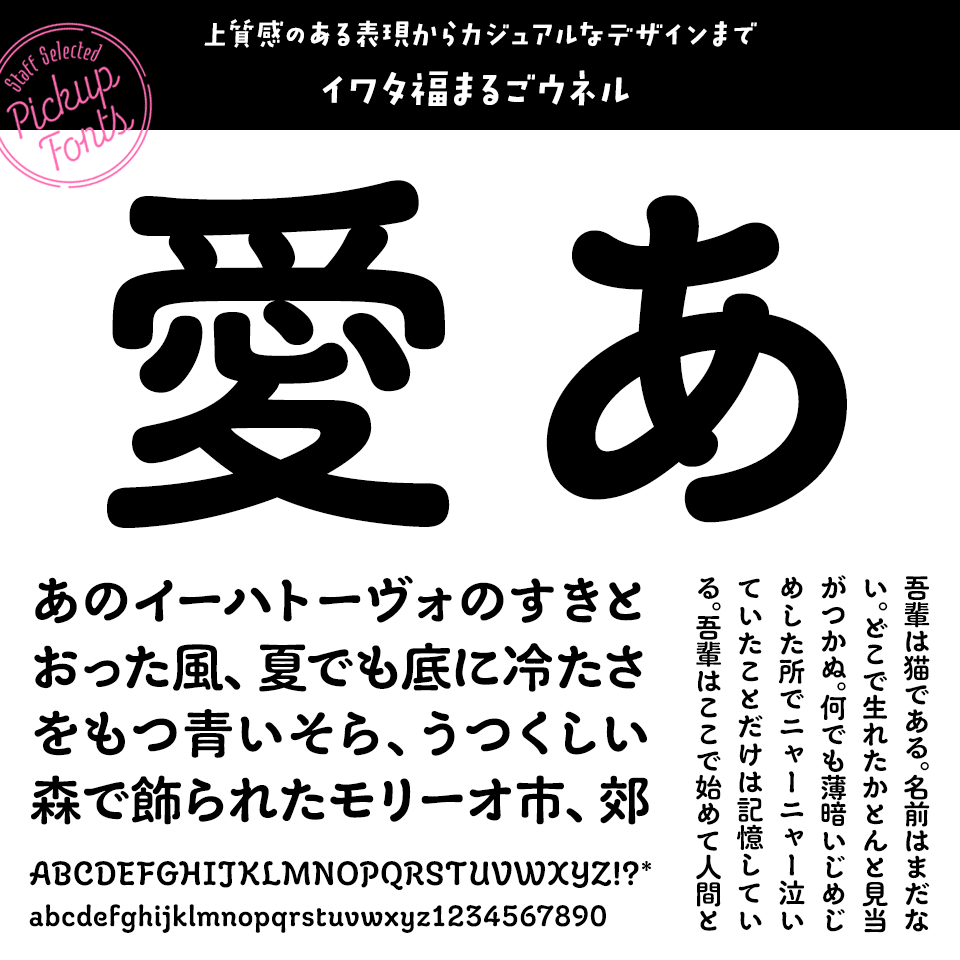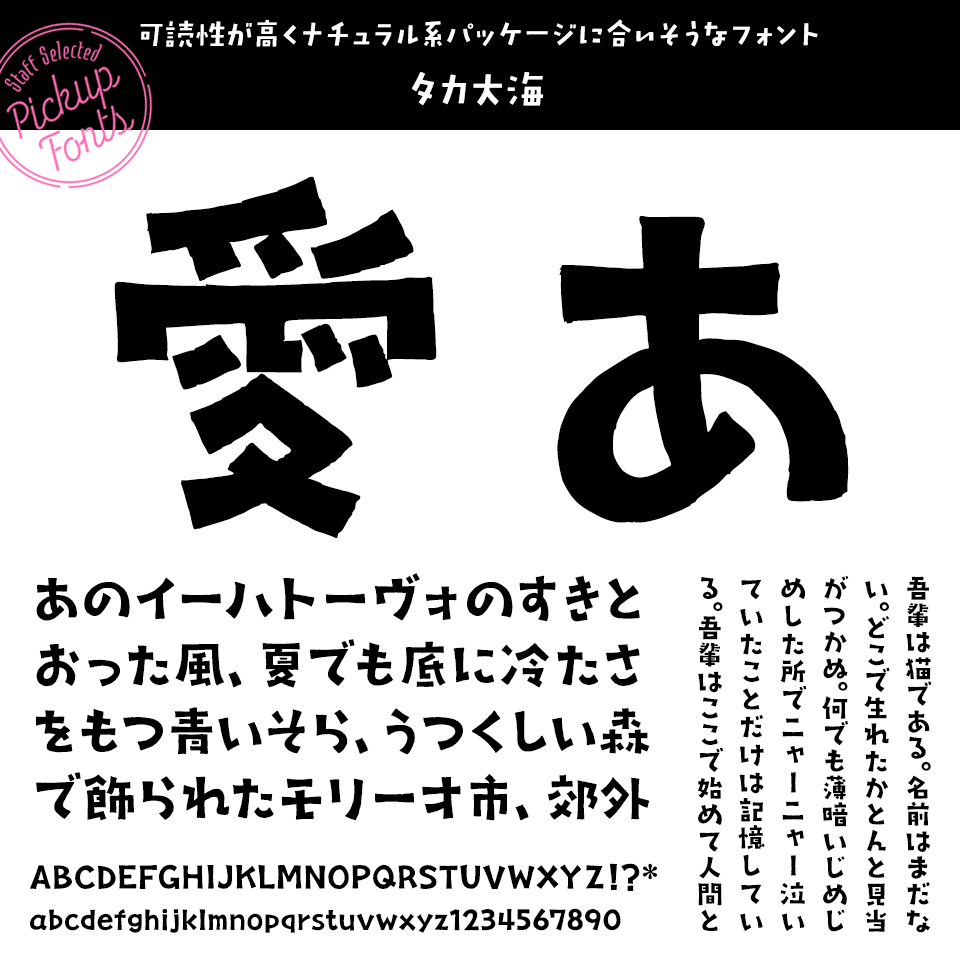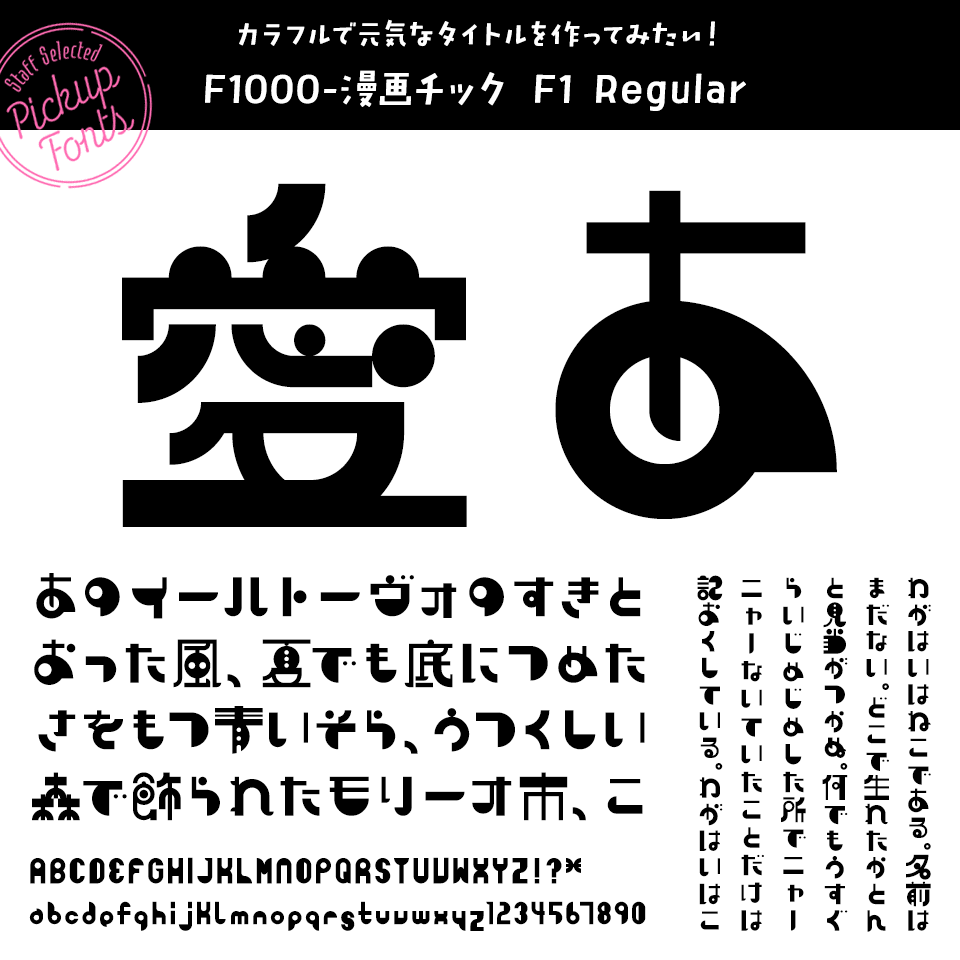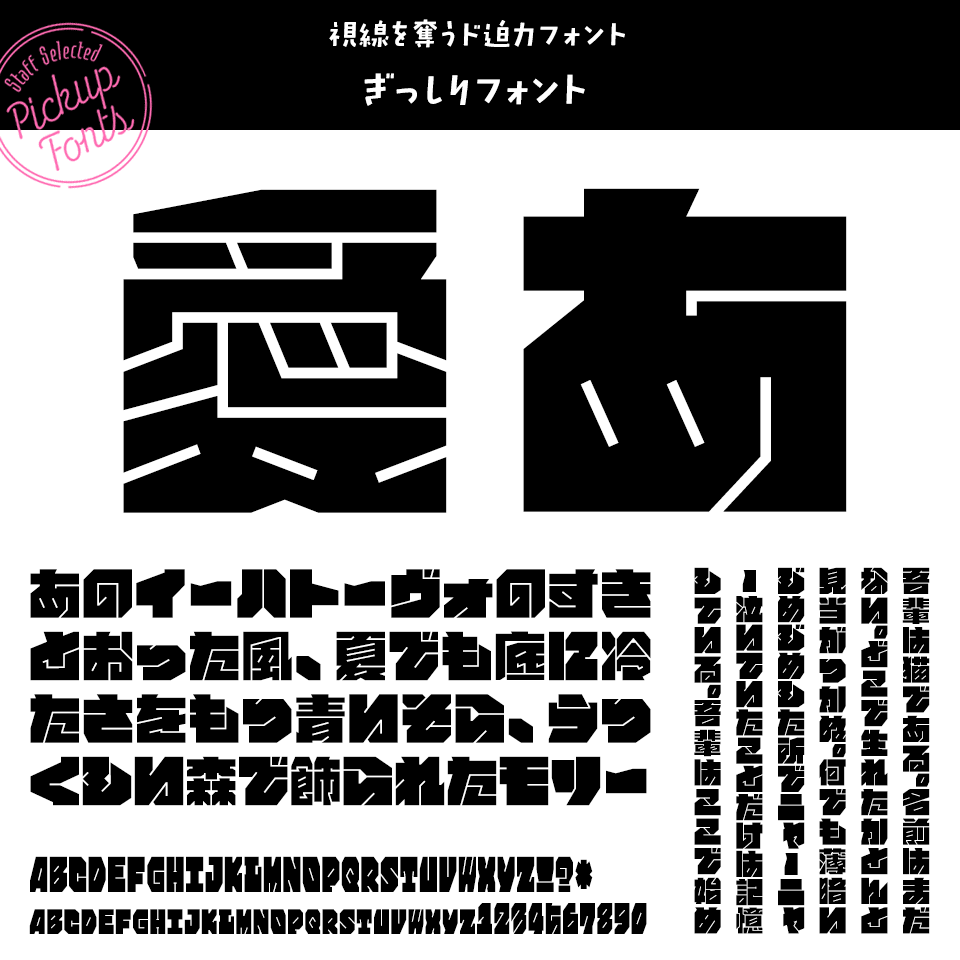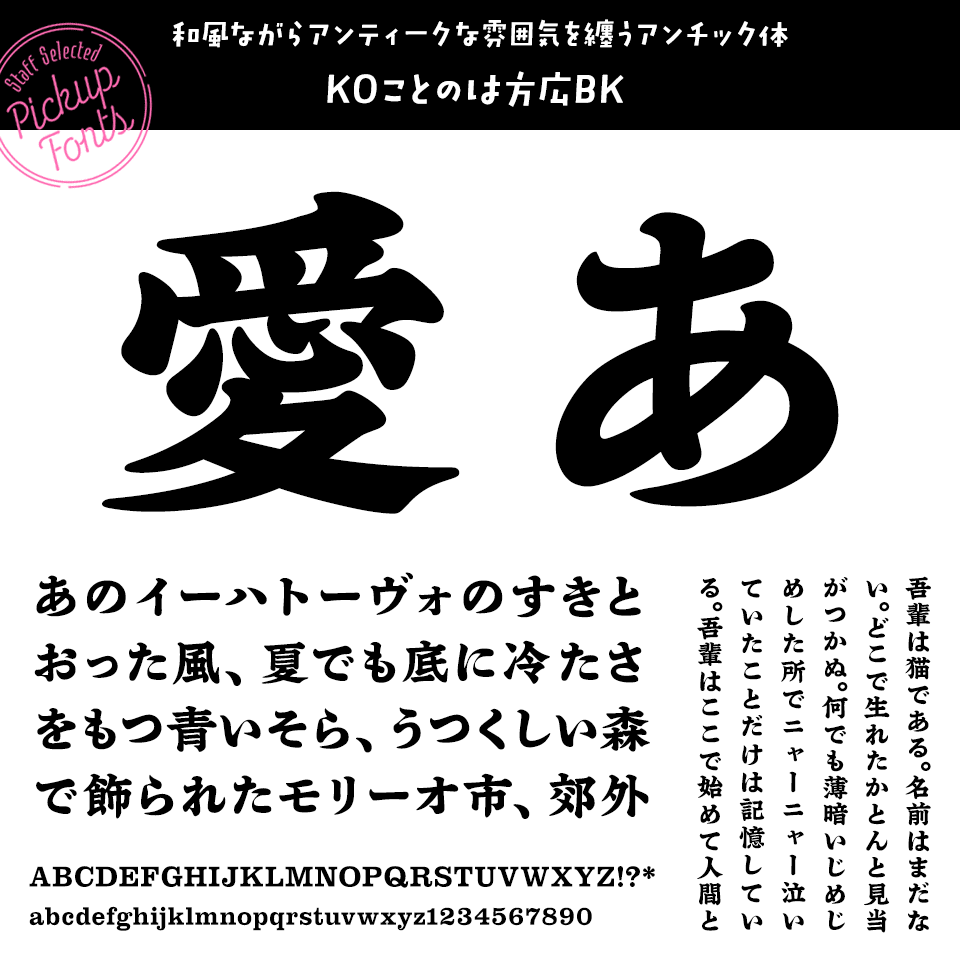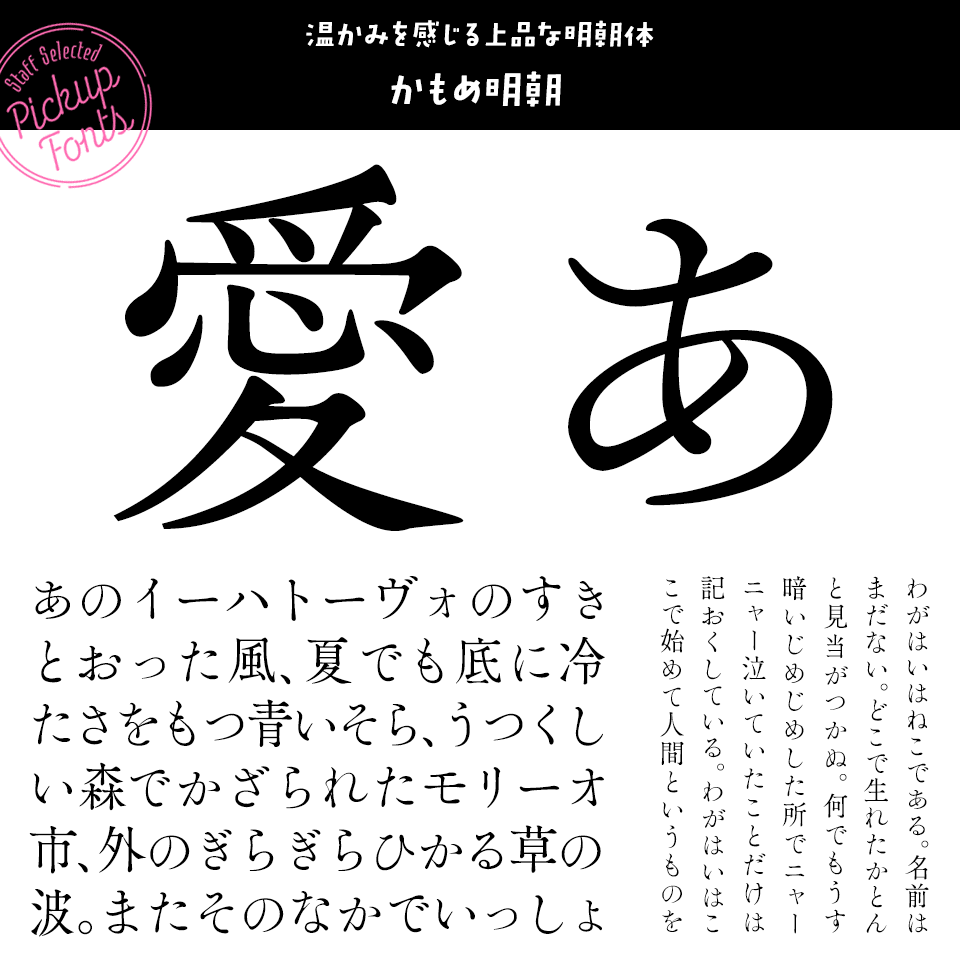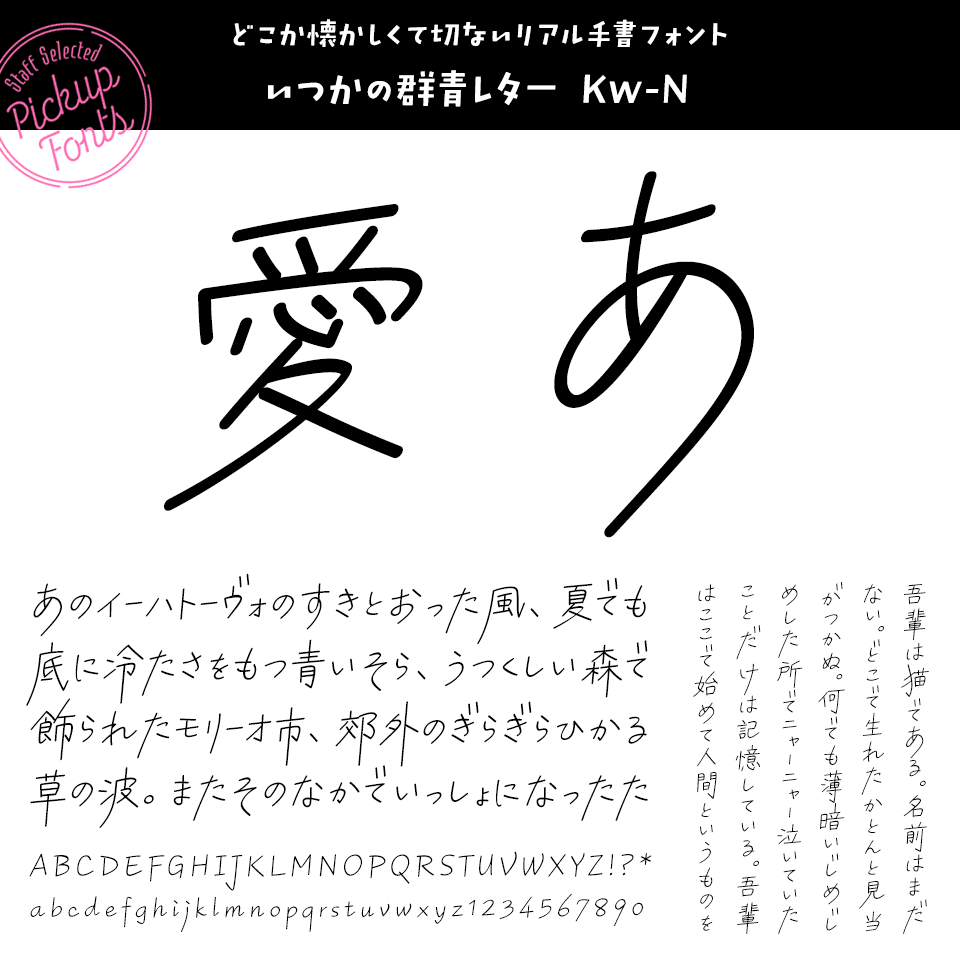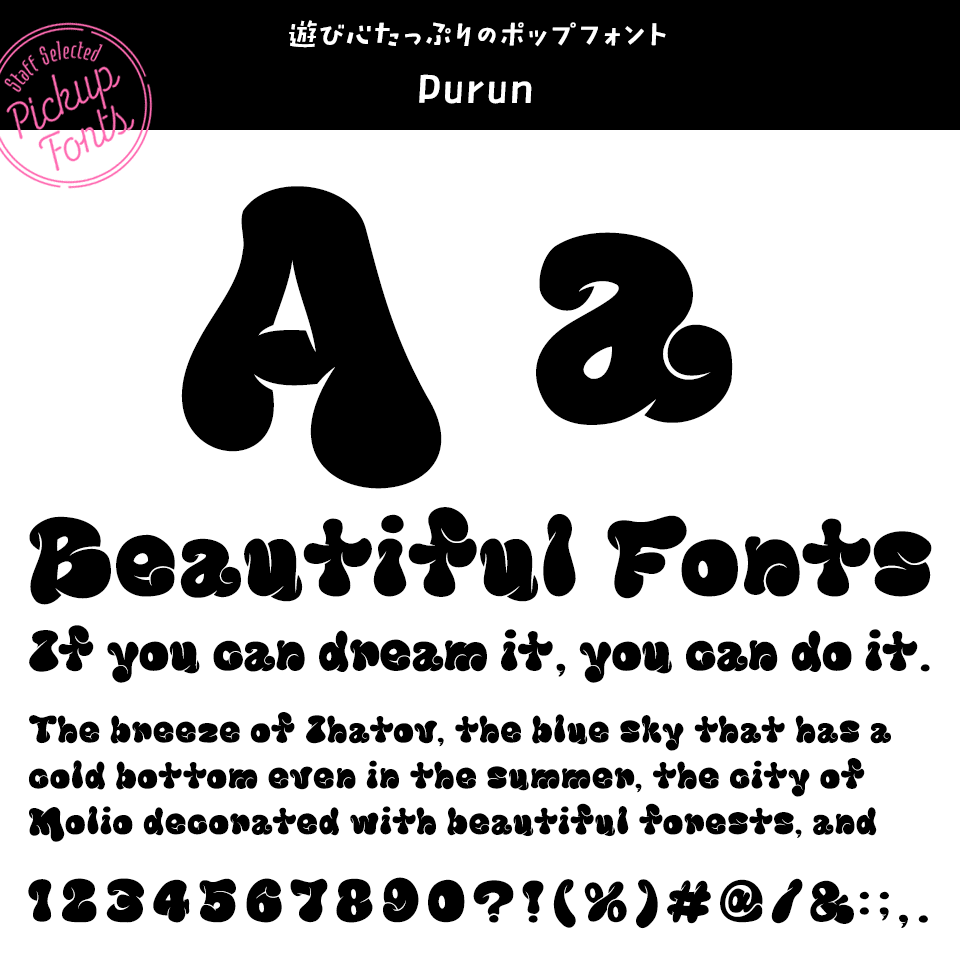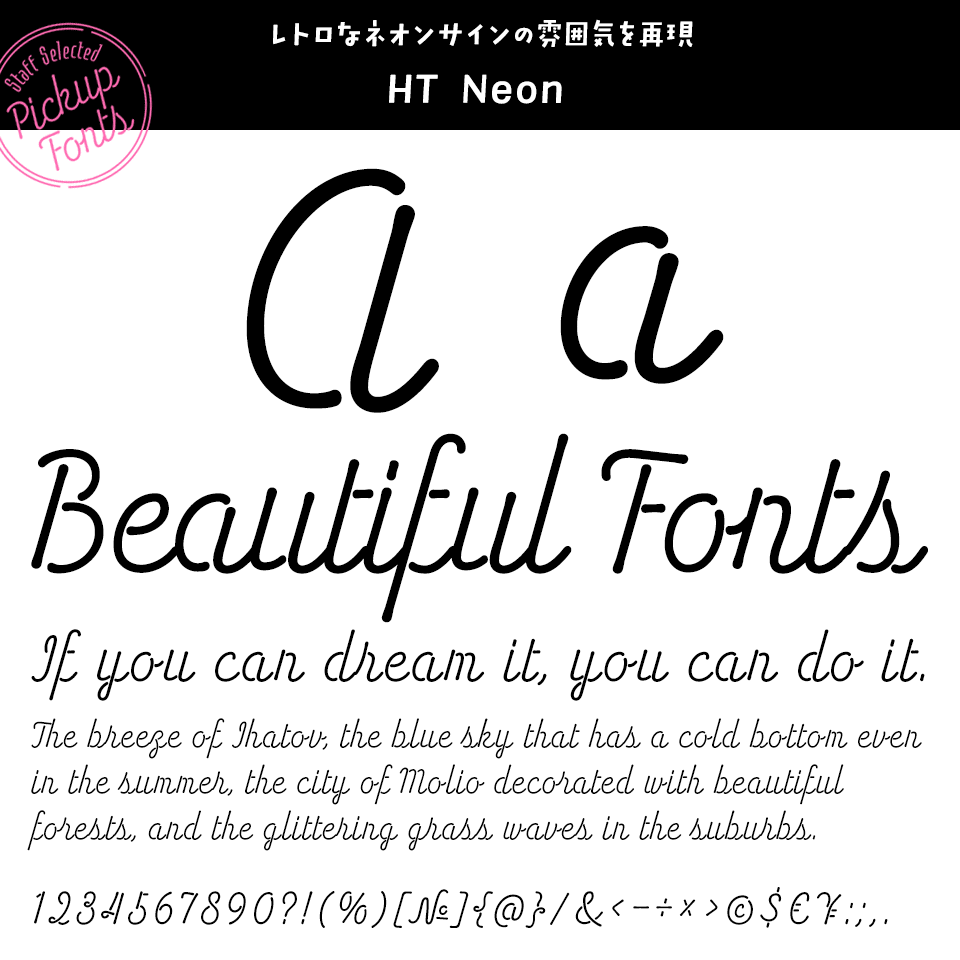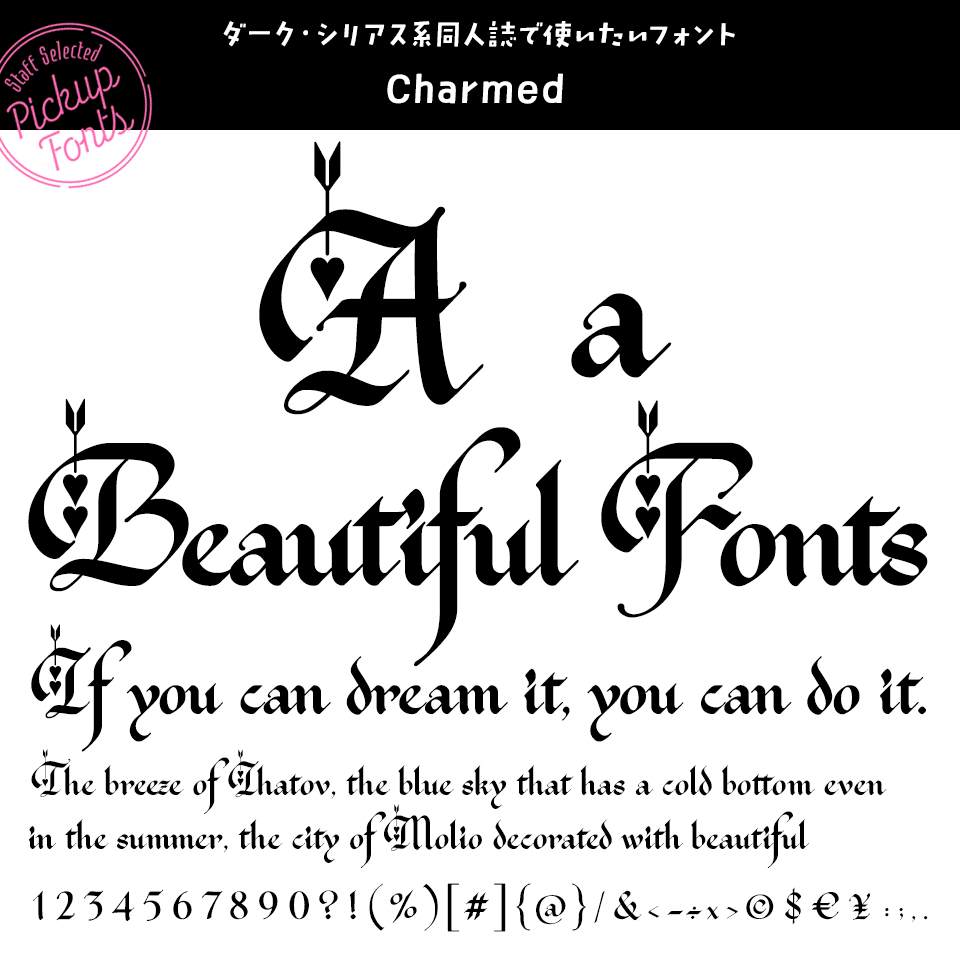
デザポケスタッフの個人的に好きなフォント イワタ福まるごウネル
上質感のある表現からカジュアルなデザインまで
デザポケスタッフの個人的に好きなフォント イワタ福まるごウネル
福まるごの「もっちりぽってり」としたやさしい丸みに、ゆるやかな揺らぎのニュアンスをプラス。上品な印象はもちろん、少しラフで親しみやすいデザインにもなじむ、表情豊かな書体です。
デザポケスタッフの個人的に好きなフォント タカ大海
可読性が高く、ナチュラル系パッケージに合いそうなフォント
デザポケスタッフの個人的に好きなフォント タカ大海
素朴で温かみのある線が特徴で、アナログ感のあるフォント。個性を出したい場面で存在感を発揮する、印象的な手書き風フォントです。
デザポケスタッフの個人的に好きなフォント F1000-漫画チック F1 Regular
カラフルで元気なタイトルを作ってみたい!
デザポケスタッフの個人的に好きなフォント F1000-漫画チック F1 Regular
コミック風の見出しやタイトル、同人誌、チラシ、動画テロップなどに向いており、作品に軽快で印象的なアクセントを加えられるフォントです。
デザポケスタッフの個人的に好きなフォント ぎっしりフォント
視線を奪うド迫力フォント
デザポケスタッフの個人的に好きなフォント ぎっしりフォント
極太で文字の密度が高く、ひと目で印象に残るインパクトが魅力のフォント。タイトルやネームボード、サムネイルなど視線を集めたい場面で効果を発揮します。
デザポケスタッフの個人的に好きなフォント KOことのは方広BK
和風ながらアンティークな雰囲気を纏うアンチック体
デザポケスタッフの個人的に好きなフォント KOことのは方広BK
辞書の見出し語などに使われていた文字をもとにした「ことのは」と、古典的な活字デザインを組み合わせており、落ち着きと重厚感のある雰囲気が特徴です。
デザポケスタッフの個人的に好きなフォント かもめ明朝
温かみを感じる上品な明朝体
デザポケスタッフの個人的に好きなフォント かもめ明朝
やわらかな曲線とほどよい余白が特徴の、温かみを感じる明朝体。上品さと親しみやすさを兼ね備えており、文章をやさしい雰囲気に整えてくれます。
デザポケスタッフの個人的に好きなフォント いつかの群青レター Kw-N
どこか懐かしくて切ないリアル手書フォント
デザポケスタッフの個人的に好きなフォント いつかの群青レター Kw-N
ノスタルジックでエモい雰囲気を持つリアル手書フォント。オシャレなInstagram投稿からオリジナリティな同人誌まで活躍する使えるフォントです。
デザポケスタッフの個人的に好きなフォント Purun
遊び心たっぷりのポップフォント
デザポケスタッフの個人的に好きなフォント Purun
太さと装飾性を兼ね備えた、存在感のあるデザインフォント。細部まで個性が感じられ、見出しやロゴに使うことで作品の印象を強く引き立てます。
デザポケスタッフの個人的に好きなフォント HT Neon
レトロなネオンサインの雰囲気を再現
デザポケスタッフの個人的に好きなフォント HT Neon
古き良きイタリアの街並みや広告看板から着想を得たレトロテイストの筆記体フォント。映画・ポスター・ロゴ・パッケージなど、雰囲気づくりを重視したデザインに最適です。
デザポケスタッフの個人的に好きなフォント Charmed
ダーク・シリアス系同人誌で使いたいフォント
デザポケスタッフの個人的に好きなフォント <strong>Charmed</strong>
白雪姫の毒リンゴをモチーフにしたゴシサイズドイタリック体フォント。リンゴの形の大文字やカリグラフィーっぽい小文字に切り替えることができます。